作为设计师你在设计中应该最最常用的字体之一就是圆体字吧,圆体字字体清晰易于字体识别、端正庄重,因为笔画的拐角处、笔画的末端呈现一个圆弧状的设计比起它的“原身”黑体字多了一丝俏皮随意,是一种日常也能使用的手写体。圆体字在设计中广泛的使用在各种类标题、图书封面、招牌、广告等领域。
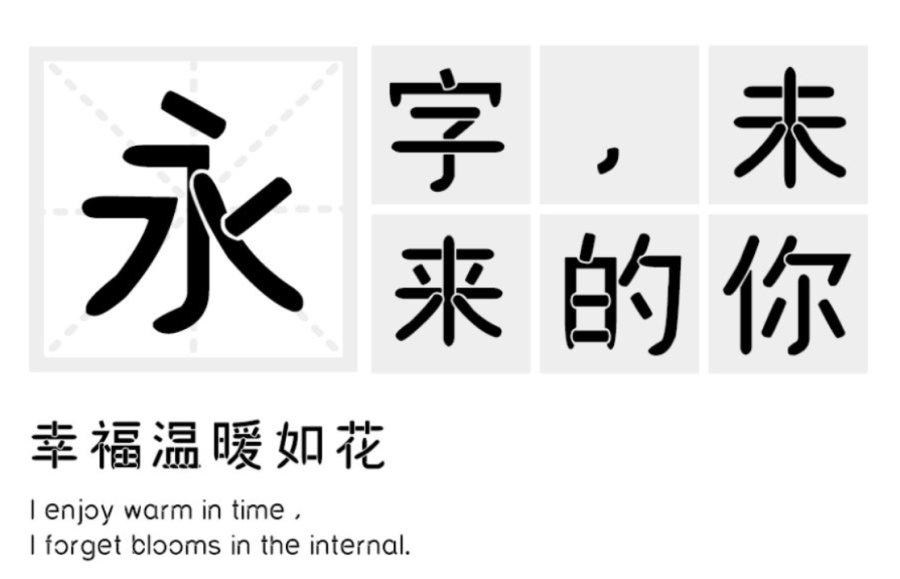
汉标赵圆粗体:这款字体具有浓厚的现代特点属于创意字体,整体方正,字体圆弧状线条像是拼接而成,展现出字体生动、有趣、可爱的一面。并且采用中宫放大原理,简约、时尚、优雅,提高功能性。适用于导视系统、VI、新媒体等领域。
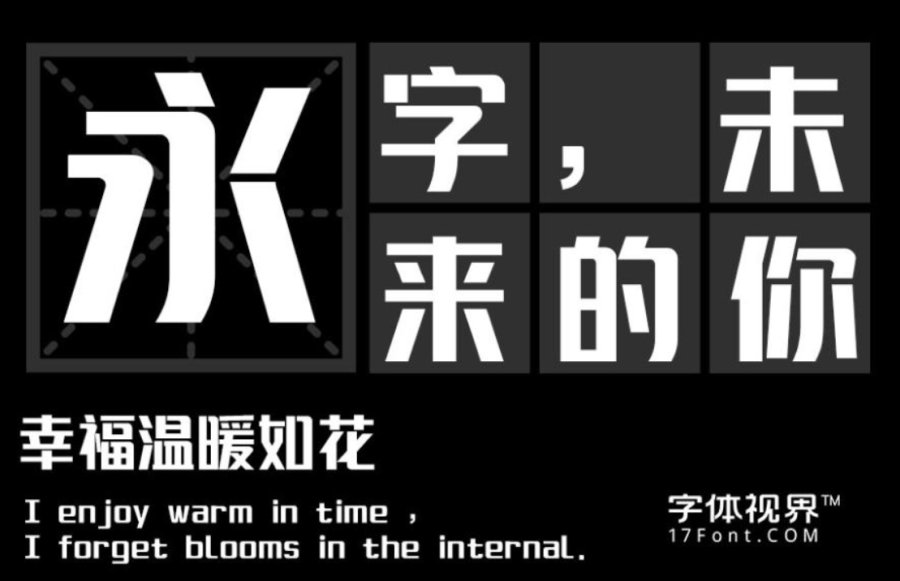
上首锐圆体:上首锐圆体,字体风格锐利偏粗壮,显得庄重,但却在转角处导圆角增添了字体的活跃性,而且字体中有断开处,使字体显得生动。适用于标题、logo设计、印刷、包装设计等领域。
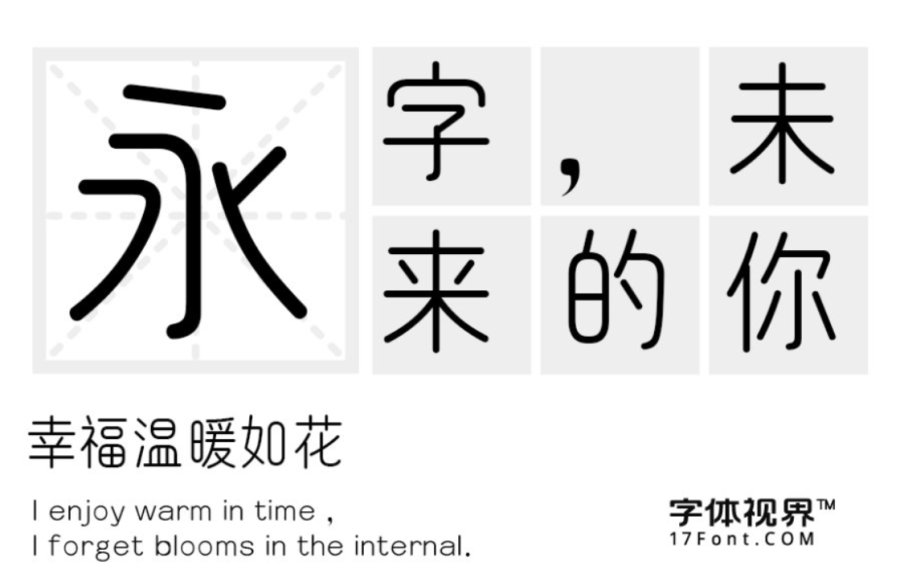
三极古圆体:三极古圆简体作品整体风格独特,具有古法圆通、朴拙之感,字形融合了象形、篆书等古朴字形,使其风格简洁明快,独具一格。字体轻巧简洁,古拙而不凡。粗细匀称,起笔收笔为圆头,折、钩、撇捺转折圆润饱满,具有古拙婉转的气质。视觉效果简洁易识别,实用性强。
实际上圆体字是国内的一种说法,在英文书法并没有圆体这一说。圆体字笔画粗细没有明显的变化和华丽的修饰,但是给人的观感更加舒适自然不失醒目。适用于各种设计类型,作为设计师的你不下载一款舒适百搭创意十足的圆体字吗?心动不如行动,赶快搜字体下载属于你的圆体字吧!